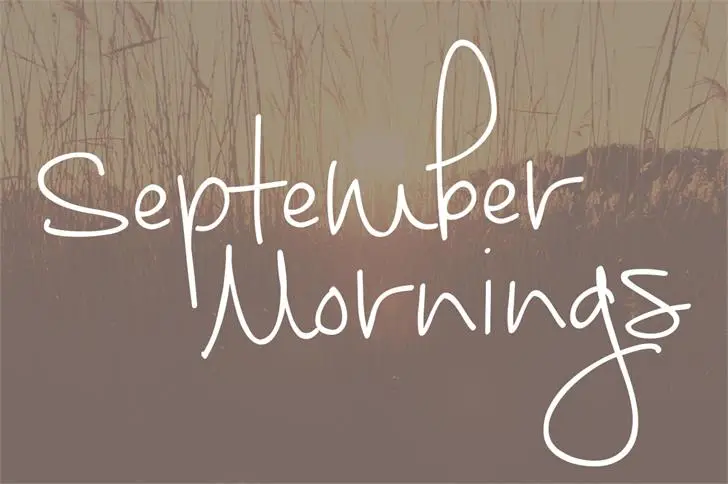
A fonte September Mornings é uma delas criada por Brittney Murphy Design em 2015, apresentando uma proposta única para os amantes do calligrafia. Esta fonte chamou a atenção com sua elegância e detalhe cuidadosamente projetado, especialmente indicada para textos ornamentais e design de gráficos que valorizam elementos artísticos e sofisticados. Perfeita para designers apaixonados por estilo clássico, September Mornings oferece uma maneira criativa de introduzir um toque distintivo em qualquer projeto. Com seu design cuidadosamente construído, você pode usar esta fonte com confiança em anúncios, capas de livros, cartazes e muito mais. A Hamilton Design categoriza a September Mornings como um fonte de calligrafia, refletindo perfeitamente o conceito de design gráfico que valoriza os detalhes artísticos. Para quem busca uma maneira única de incorporar elementos de arte em seu trabalho visual, esta fonte é perfeita. September Mornings não apenas oferece uma paleta colorida variada para escolher a melhor opção para seu projeto, mas também assegura um resultado que reflete o cuidado meticuloso aplicado nas linhas e formas da letra. Esta é uma excelente adição para qualquer designer profissional em busca de novas maneiras de expressar sua visão criativa no design de gráficos.